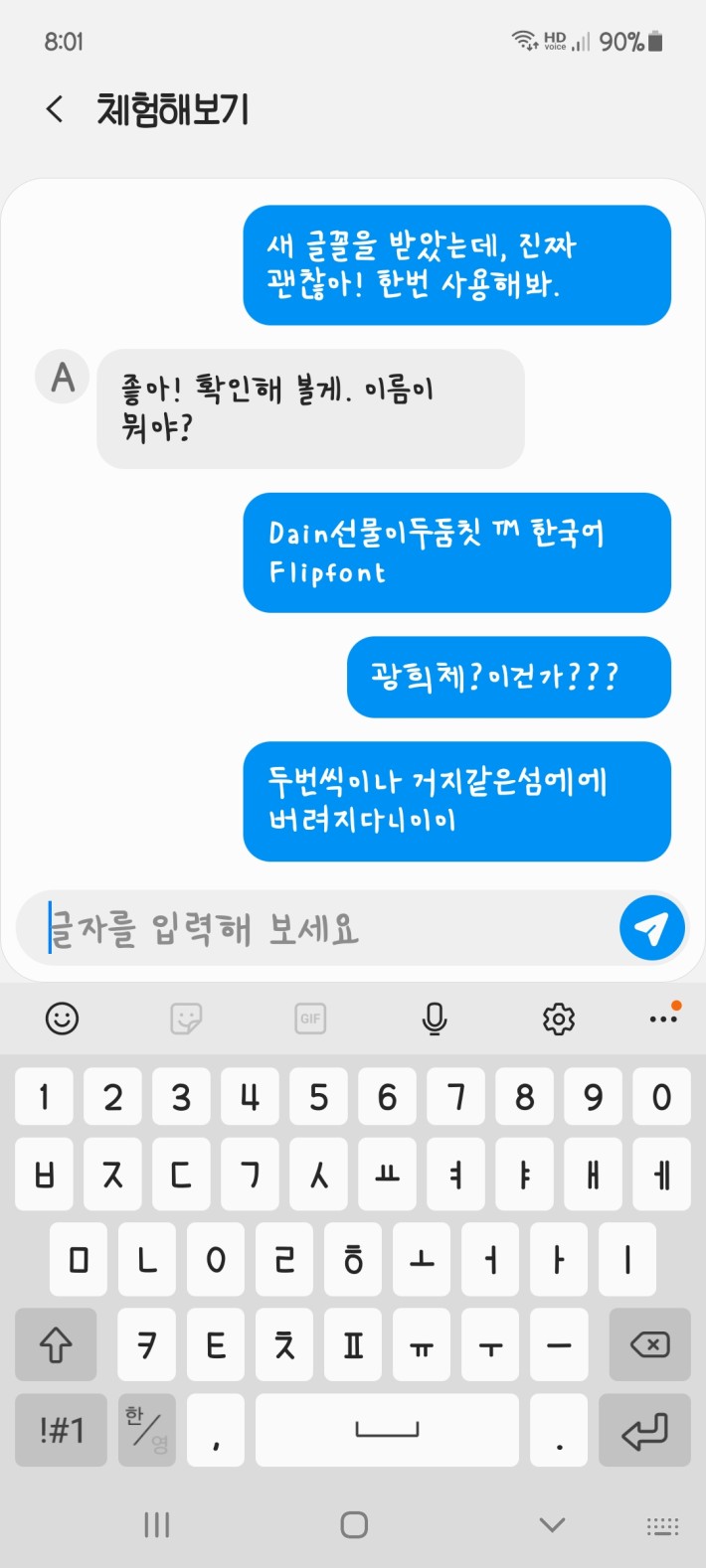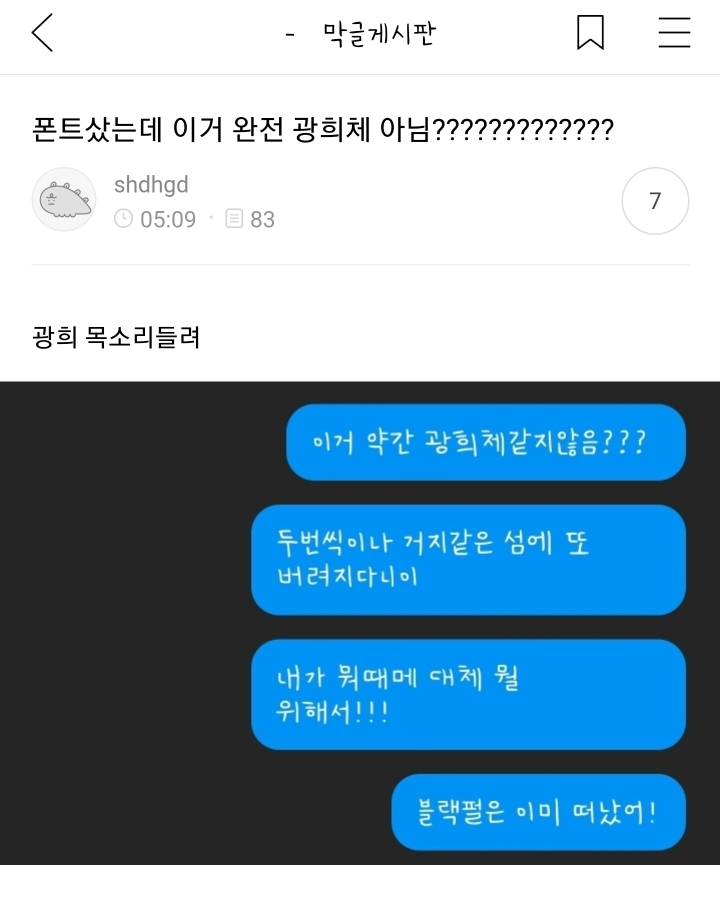
광희체 음성지원, 폰트를 샀는데 광희 목소리가 들려
활자가 팔랑거리는 광희 팔다리 같어..
광어체
전혀 그래보이지 않음
별로인데...하나도 광희같지않음
@홍구땡구누룽이 직접 찾아보니 이거같습니다 ㅋㅋㅋㅋ 귀엽네요 ㅋㅋㅋ
극혐체이군
그래서 저 폰트가 뭔가요?? 진심 엄청 이쁘다고 생각하는디????
그래서 이 폰트가 뭔대요ㅠㅠ!!!